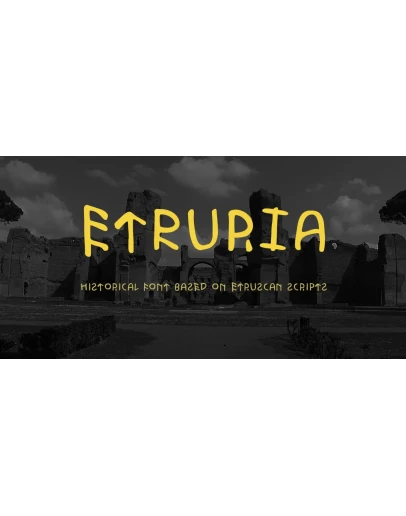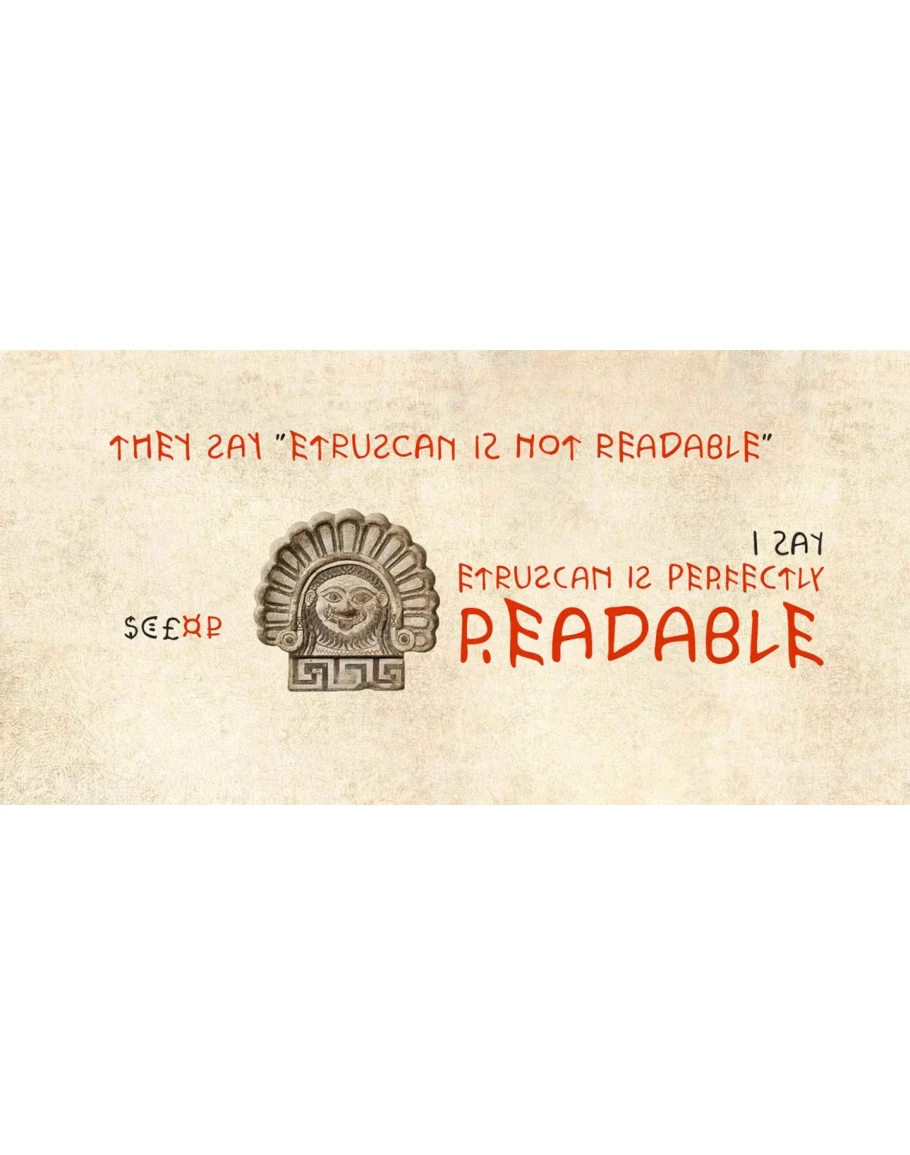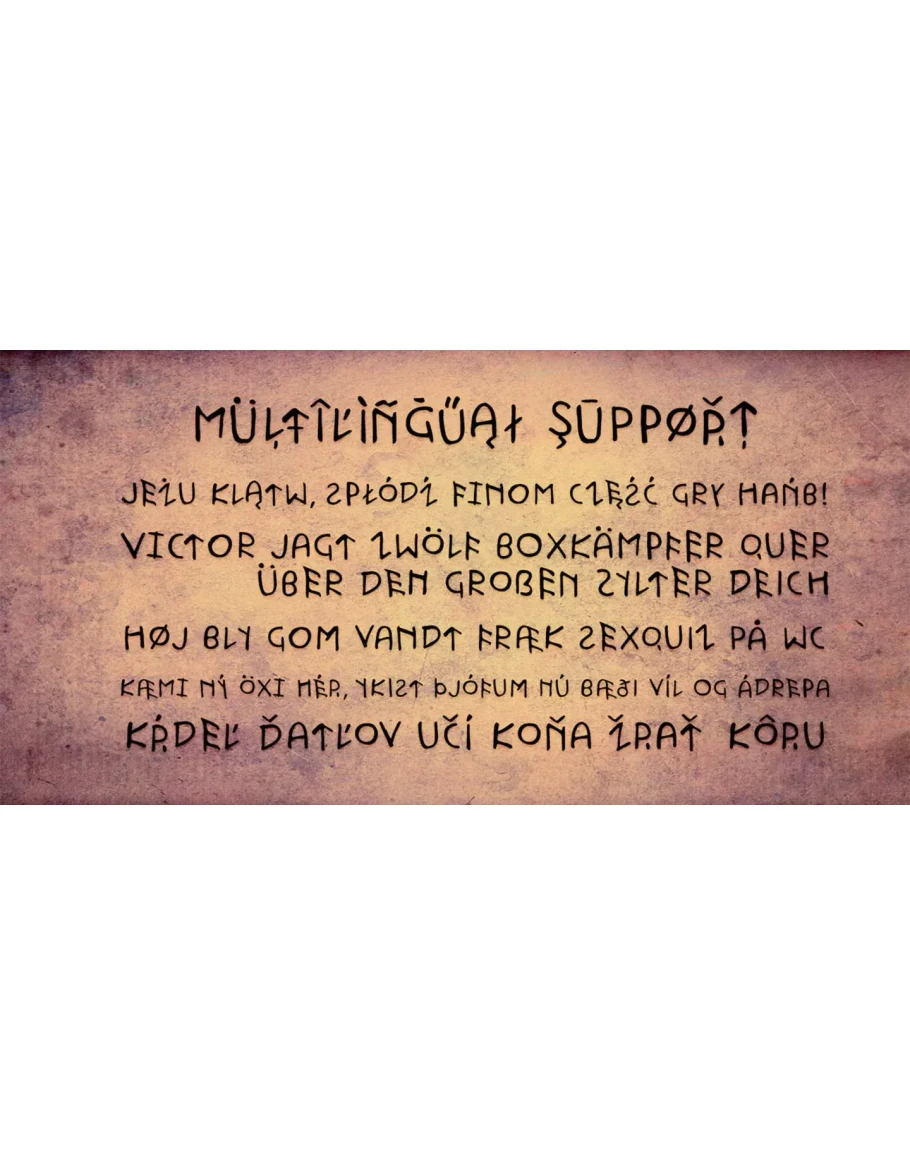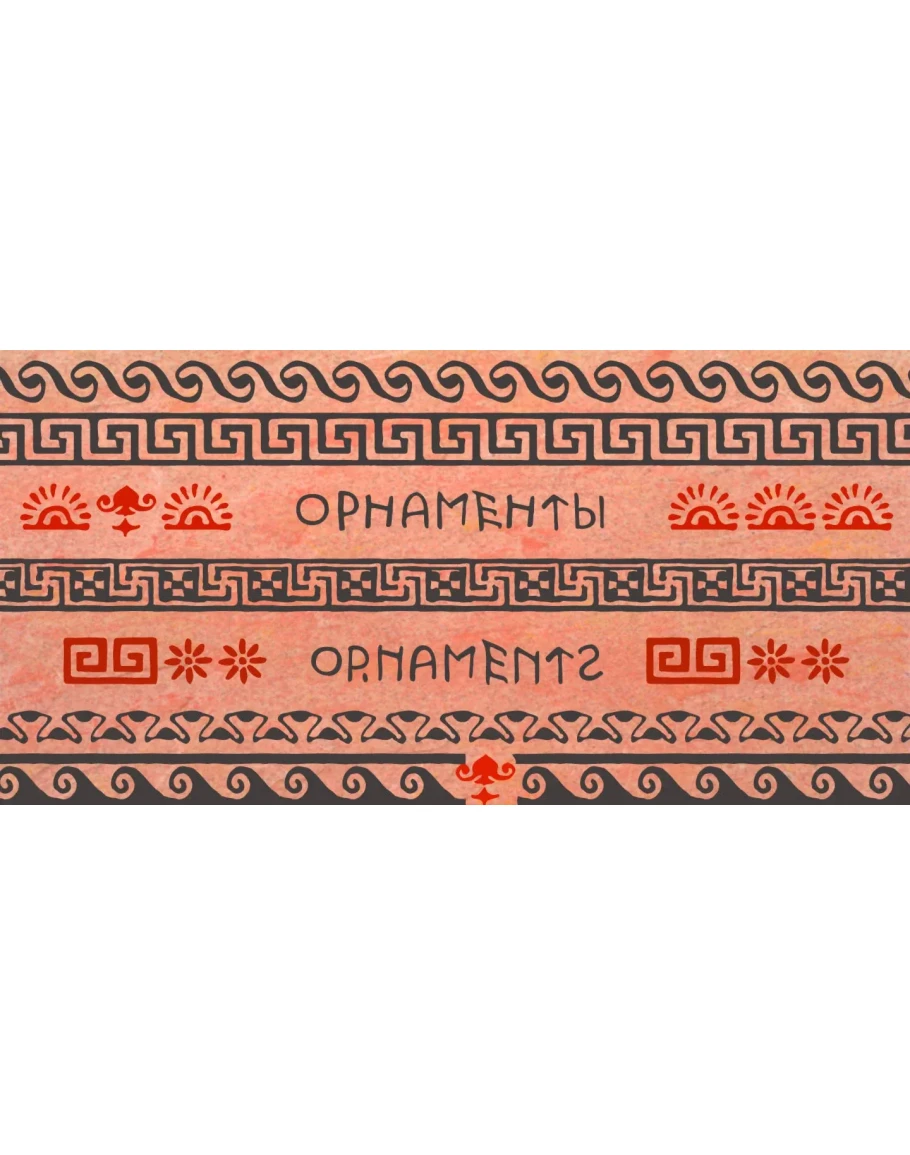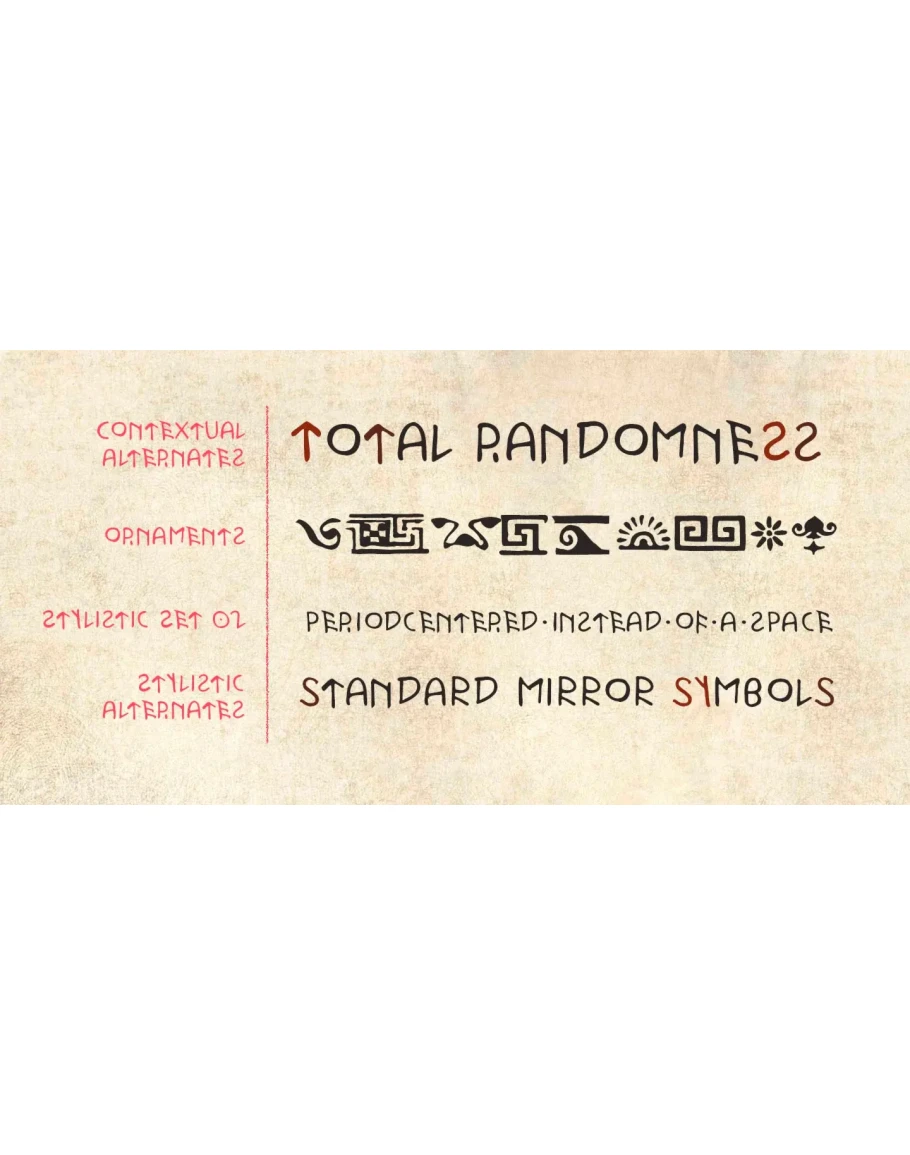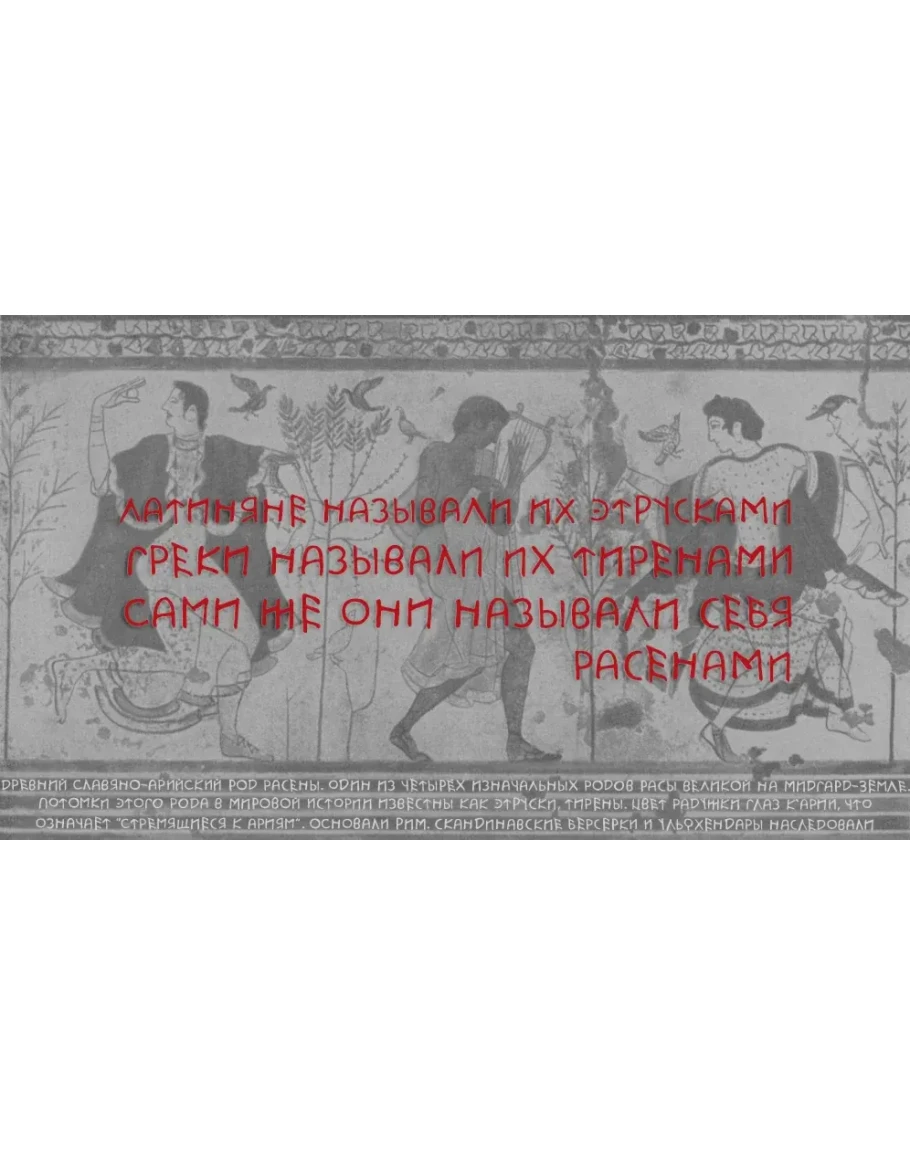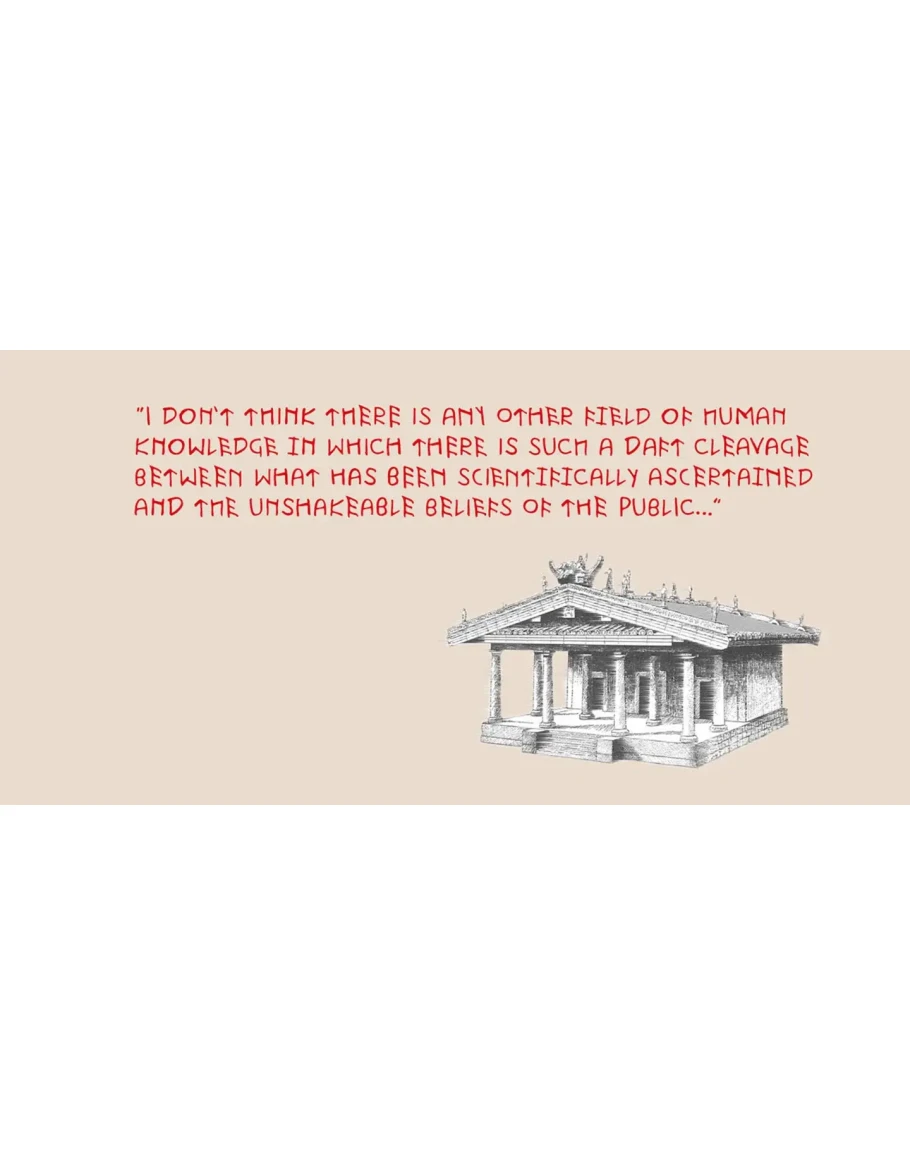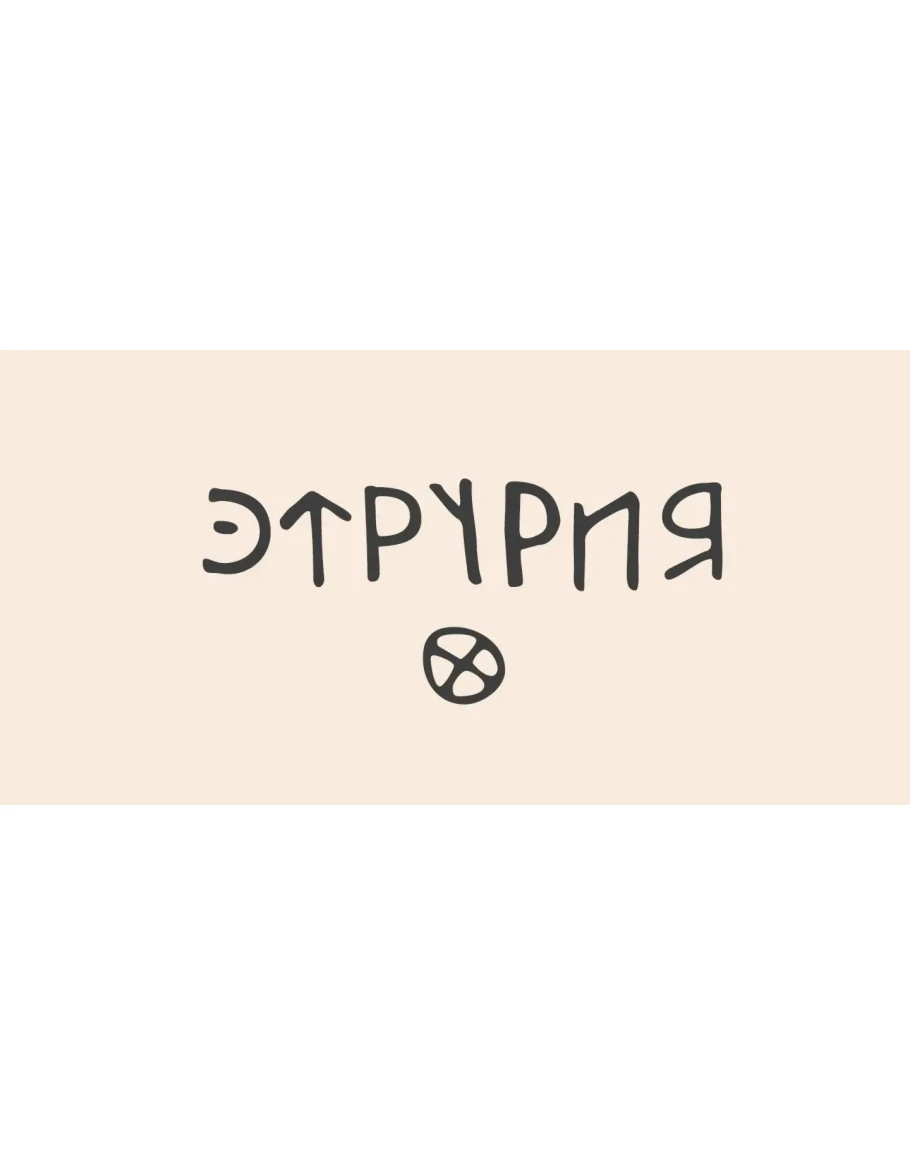
Шрифт Этрурия основан на Этрусских письменах и реалистично точно имитирует письменность Этрусков. Замысел шрифта Этрурия - дать возможность любому человеку прикоснуться к прошлому человечества!
Все ОpenТype-особенности можно использовать вместе, по отдельности или вообще отключить.
Вообще главная характерная черта Этрусских надписей это неповторяемость и разнообразность символов. Отличающиеся строчные от заглавных это лишь первый шаг на пути к созданию эффекта неповторяемости букв. Дальше на помощь приходят ОТ особенности. Чтобы воссоздать эффект случайности, я использовал несколько ОТ особенностей (контекстные альтернативы, стилистические альтернативы и стилистические наборы), в которых встроен скрипт для имитации случайности. Дополнительно другой скрипт создаёт эффект подскакивания букв. Все вместе они создают невероятно реалистичный Этрусский текст.
При этом, любую из этих особенностей можно отключить по своему желанию. Также я использовал небольшой интерлиньяж, потому как это характерно для этрусского письма.
Вообще Этрусское письмо представляет собой зеркальные письмена по сравнению с нынешними европейскими алфавитами. Я не стал использовать эту особенность во всех буквах, потому что это сделало бы шрифт сложным к восприятию, но для придания шрифту характерного Этрусского стиля, я сделал несколько букв в зеркальном отражении. Тем не менее, если для кого-то это покажется непривычным, то зеркальные буквы можно отключить, вместо них появятся более привычные.
Характер Этрусского алфавита предполагает создание шрифта с только заглавными буквами. Однако, я не стал ограничивать этот шрифт. Поэтому здесь не только строчные, отличающиеся от заглавных, но и дополнительный набор альтернативных знаков.
Ещё одна особенность Этрусских письменностей это использование вместо пробела точки. Шрифт Этрурия имеет и эту возможность, для этого есть ОТ-особенность Стилистический набор 03. Естественно, и его можно при желании отключить.
Главная цель достигнута! Текст, набранный шрифтом Этрурия, создаёт полное впечатление настоящих Этрусских надписей.